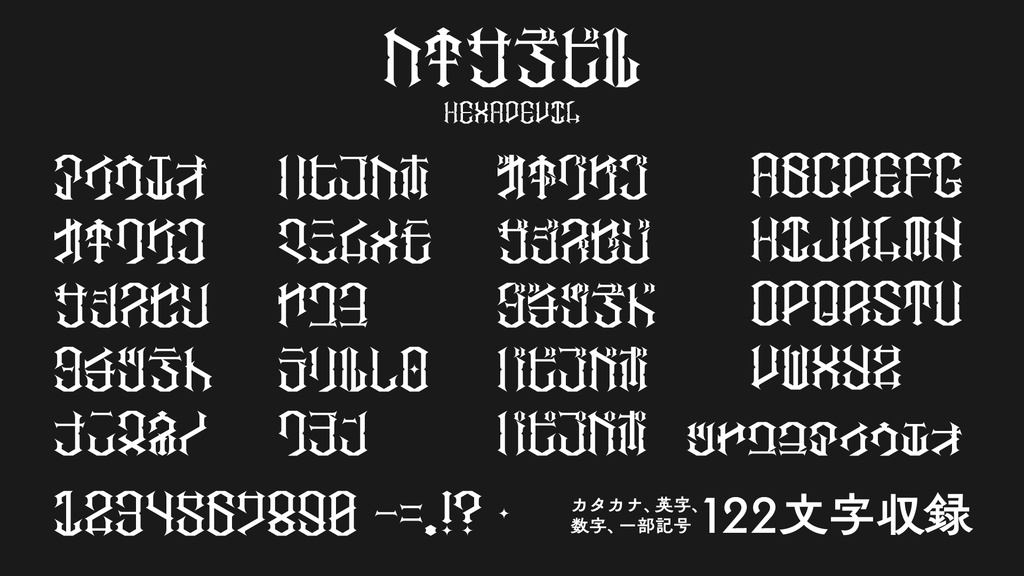
【フリーフォント】ヘキサデビル
六角形ベースのダークファンタジーを意識した少年の心をくすぐるデザインのフォントです。 カタカナなども収録しています。 ■ご利用について ・個人利用可能です。 ・以下のSNSアカウントのいずれか一つをフォローしている場合は商用利用可能です。 ・https://twitter.com/orange634nty ・https://www.instagram.com/orange634nty/ ■収録文字 カタカナ・英数字(英字は全て大文字のみ)・一部記号 122文字収録 OpenTypeフォント ■注意事項 ・使用する際は同封されている「hexadevil-readme.txt」をよく読み利用してください。 ・フォントのインストール等の技術的なサポートはいたしません。 ・フォントを使用して発生したと思われる如何なる問題についても、作者は責任を負わないものとします。 ・こちらのフォントは Fontlab 8 を利用して作られています。 ・使用する際作者への報告は不要です。ただ、報告されるととても喜びます。 ■お問い合わせ mail: orange634nty@gmail.com twitter: @orange634nty